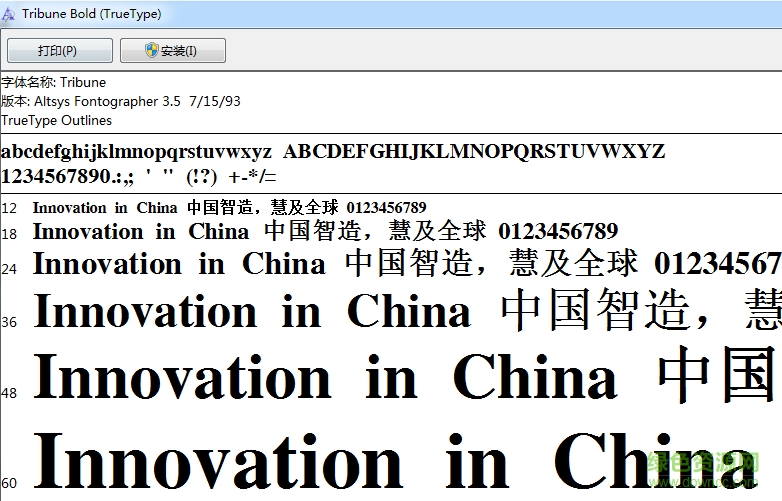
Tribune字體是英文字體庫中的個性字體,字體的線條十分標(biāo)準(zhǔn),適用于各大領(lǐng)域,非常好用的一款字體,有需要的朋友就來綠色資源網(wǎng)下載使用吧!
Tribune字體是一款個性英文字體,字體非常具有個性,能給人留下深刻印象,有需要的朋友就趕快來綠色資源網(wǎng)下載吧!